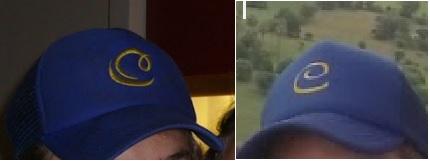
Suche Schrift für eine Mütze
ich möchte für einen Freund eine Mütze besticken lassen. Eine ähnliche Mütze existiert bereits mit dem Buchstaben "C" (in zwei Versionen).
Damit die Mützen zusammen passen, suche ich die Schrift(en), welche auf den Originalen verwendet wurde(n).
Erkennt Ihr eine der beiden Schriften?
Wurden die Buchstaben auf obigen Bildern denn definitiv mit Schriften erstellt? Oder ist das vielleicht irgendein Team-Logo oder sowas?
bei dem rechten Bild auf jeden Fall als Schrift.
Bei der linken Version bin ich mir nicht sicher.
Wenn jetzt schon die beiden Cs auf den oben gezeigten Bildern nicht zusammenpassen, was genau wird dann eigentlich gesucht? Ein irgendwie ähnlich geschwungenes C?
PS: Ich musste gerade an das hier denken ...
ich suche die Schrift die bei dem "C" verwendet wurde (entweder von dem linken oder von dem rechten Bild).
Wenn ich die Schrift habe kann ich ein entsprechendes "K" raussuchen, welches auf die nächste Cap gedruckt werden soll.
Beim Besticken ist doch die Umsetzung einer Vektorzeichnung in ein stickbares Programm das, was den Großteil der Kosten verursacht. Frag doch mal bei einem Besticker nach, der hat bestimmt unzählige stickbare Schriften mit seiner Stickmaschine gekauft und da ist sicher auch irgendwo ein geschwungenes C dabei.
Da wäre doch spannend zu erfahren, woher das Design stammt – vom Auftraggeber oder vom Besticker?